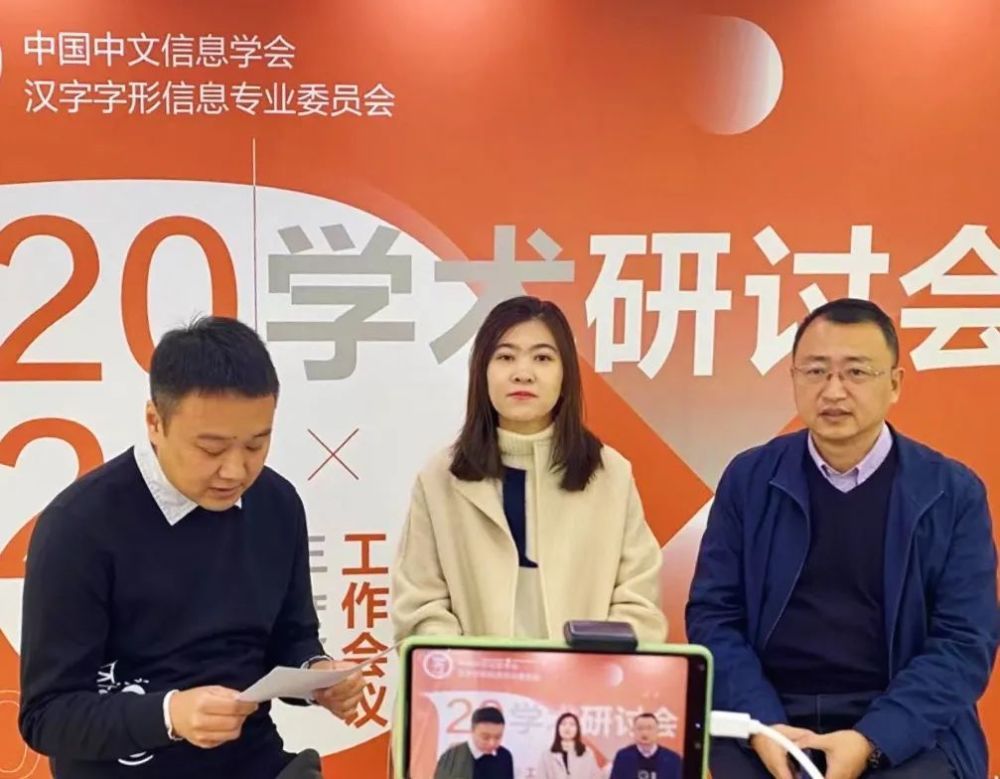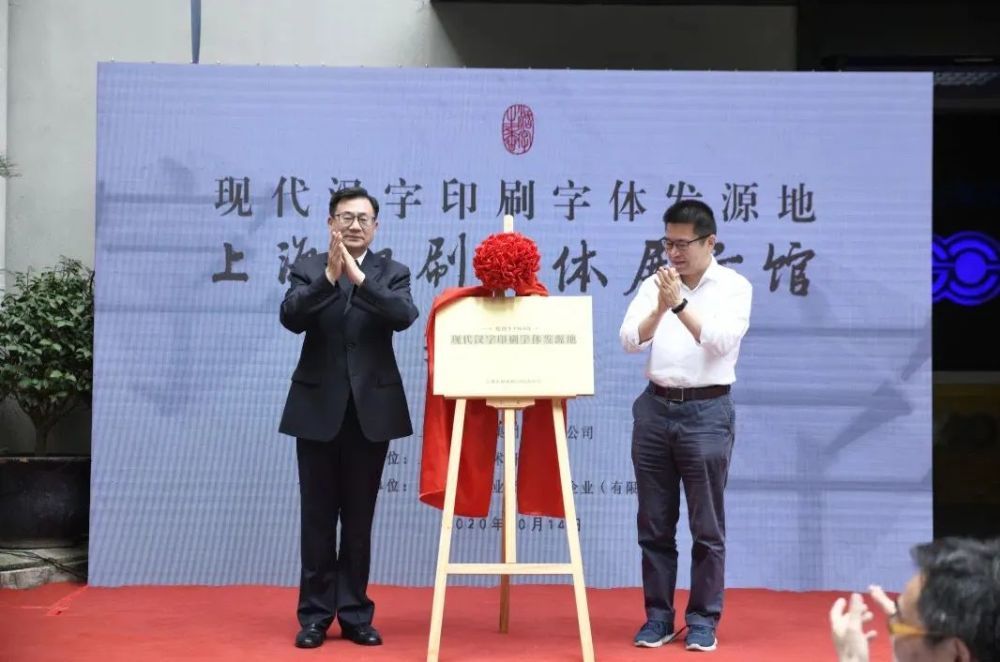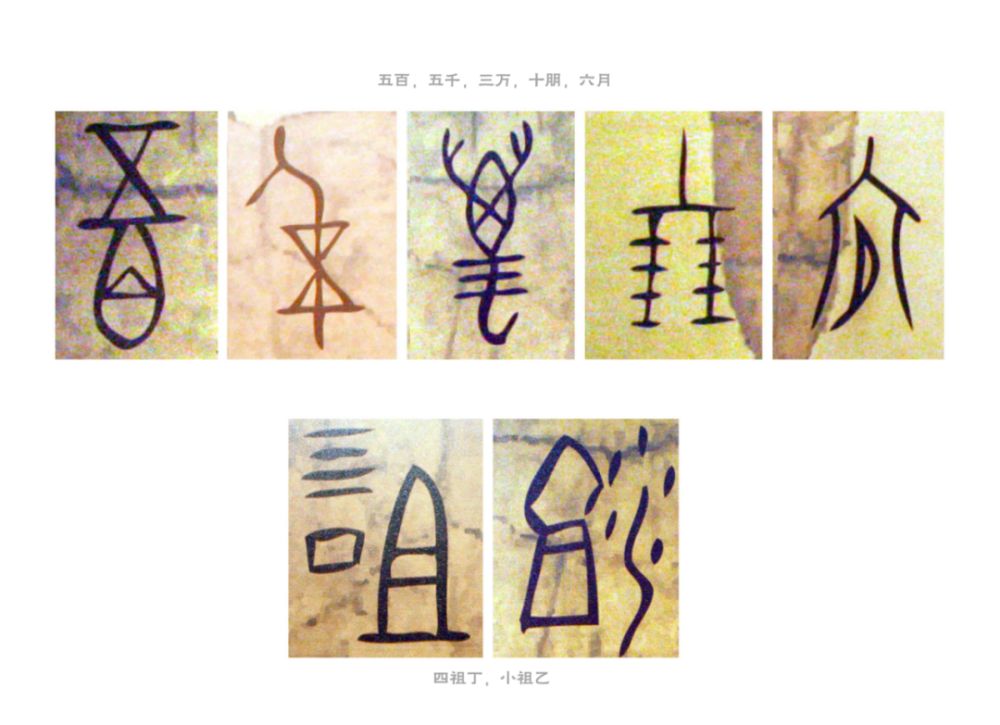
2020年汉字字形学术研讨会通过线上会议方式顺利举办
原文标题:干货回顾丨字体业者线上齐聚,共话文字设计新发展
12月6日,由中国中文信息学会汉字字形信息专业委员会主办的“中国中文信息学会汉字字形信息专业委员会2020年学术研讨会”圆满结束。数十位中文字形信息领域的专业从业者、研究者、字体厂商代表,以及两百多名来自全国各地的字体设计爱好者以线上会议的方式共同参加了此次学术研讨会议。
中国中文信息学会办公室主任肖千慧(中)出席会议并致辞
汉字是中华文化的基因和核心,是中华文明得以传承和发展的载体,而计算机中文字体是汉字书写文明在信息化时代的全新表现形式,也是中文信息处理的基础,是最具中国特色的知识产权产品。中国中文信息学会一直多方呼吁加强字库知识产权的保护。近年来,在各方的共同努力下,字库行业开始进入良性发展阶段。
肖千慧老师还表示:希望在专委会各位委员,在所有专业从业者、研究者的共同努力下,推动中文字形信息学科的发展,传递汉字之美,弘扬中华优秀传统文化。
下面,就让我们一起来回顾这场字体云盛会的干货内容吧~
《汉文正楷在东亚地区的传播、影响及再设计——纪念汉文正楷诞生90周年》
汉文正楷是1930年代在中国上海诞生的著名的楷体活字,共包含11种字号和样式,是民国时期的第一套足体的铅活字。
汉文正楷一经面市便颇受欢迎,不久便被日本芦泽印刷所、金田三省堂等购入到日本进行销售。日本活字工业、IWATA、MOTOYA等著名活字公司都进行过改刻,可以说日本的正楷字体深受汉文正楷的影响。这些改刻和再设计贯穿了铅字时代、照排时代和数字时代。并流传到中国香港、中国台湾和东南亚地区。
本次演讲对汉文正楷的历史进行了研究、展示,通过收集、整理跨越了90年的资料和文献,为汉文正楷的数字化再设计提供了详实的参考和依据。
为打破当时外国资本对楷体活字的垄断,郑午昌等人创办汉文正楷印书局,并委托中华书局编辑高云塍书写了八千多字楷书原稿,此为汉文正楷的缘起
佐藤敬之辅巨著《汉字》中记录了日本活字工业对汉文正楷进行改刻的内容,主要包含三个方向:1.扩大中宫,缩小字面;2.将撇捺斜钩等笔画进行了缩短;3.横笔画的斜度更加统一,增强字体的稳定性。
对汉文正楷的再设计,遵循了中国大陆楷书字体的规范结构及笔画特征,同时对原字不理想的部分进行了修整
《汉字印刷字体的文化传承》
作为国内最早建立汉字印刷字体书写基地——上海印刷技术研究所数十年来始终在努力宣扬、保护和传承字体文化的道路上坚守前行。今年10月上海印研所举行了“现代汉字印刷字体发源地”和“上海印刷字体展示馆”的揭牌仪式,希望通过追本溯源、还原历史,尽可能让更多的人走进字体、关注字体、了解字体。
字体设计作为一项文化传播性的工作,应该将其纳入到美育的行列中,具有前瞻性和延展性的教学理念是推动行业发展振兴的关键性因素,能全方位的培养人才,夯实行业基础,在将文化与设计不断相融合的过程中,也引导大众建立起正确的字体文化属性,了解字体以及字体设计背后的故事,提高字体设计专业领域的社会认知度,将我们的汉字文化代代相传。
上海印刷技术研究所为现代汉字印刷字体的创写与发展做出突出贡献
“现代汉字印刷字体发源地”和“上海印刷字体展示馆”的揭牌仪式
上海印刷字体展示馆
《中国佛教文化字体设计(对佛经手抄本和刻本研究进行数码复刻)》
佛教是中国最具影响力的一个教派,二千多年来,对我国的各个领域都产生了深刻的影响,书法作为一个特殊艺术形式也不离外。在印刷术出现之前,僧人、信徒在读经之余抄写经文,以此来传播佛教的教义和扩大佛教的影响。由于纸、帛易于损坏,不便保存,就有一些佛教徒把经文刻在山崖或石碑上。在印刷技术出现后,佛教徒也通过刻制经板印刷经书的方式进行传播。
写经和刻经,对中国书法艺术和印刷技术都有着深远的影响,通过对古代经典进行研究来探索现代汉字设计新的可能性。传统文字、文物受载体的限制难以保存和展示,字体文物存在永久性损坏或遗失的风险。
本次演讲展示了通过对古代经典写经、刻经进行复刻,将文字文物转化为数码字体的研究成果,希望能够利用字库产品在互联网环境中的通用易用的性质,使文物的文化价值得到最大化的传播和体验。
汉仪敦煌写经的佛经写本原型文字
汉仪北魏写经的复刻对照
汉仪金陵刻经字体
《北碑正书 | 设计思维下的多域文明碰撞》
北碑正书以方笔入字,将笔画的婉转变化,起承转合,用刀刻直线转折,代替笔画线条转折。壮其胆、强其骨、厚其力、生其势。其灵感来源于北魏诸家碑体,与古苏美尔人的楔形文字。本次演讲通过展示北碑正书的设计过程,呈现现代思维下的多领域(古今、中外)文明的碰撞。
北碑正书
为字体添加视觉锚点的两种情况
北碑正书字形展示
《最新中文字体设计交流与分享-互联网与智能时代汉字字形探索与研究》
字玩实验室是锐字旗下一个致力于探索汉字创新设计与研究的实验室,探索汉字的N种可能,研究汉字设计的未来发展趋势,研究汉字设计与新场景与新技术的融合。本演讲分享了字玩实验室的一些字体研究成果:
1.字玩实验室推出了全球第一个智能代码72变系列化中文字库,字玩汉字设计引擎可以一键生成符号、标准中文编码的新字形。
2.字玩不明黑与字玩不明宋是在现有汉字构成规律的基础上,字玩实验室尝试做出一些新的汉字字符,这些字符即保留了已有中文的特征,也有独特的组合方式。另外,通过不同部件的结合方式,也让这些新字符营造出不同程度的熟悉感或陌生感,字玩不明黑与字玩不明宋采用中文5000个字对应的编码生成字库,可以直接使用与应用到文化衍生设计中。
3.字玩翻滚积木彩色字库是全球第一款中文彩色积木字库,采用中文简体标准编码,可以直接使用Adobe及支持彩色字库的软件上使用,可以自定义专色。彩色积木字库是在探索黑白字体与场景新字形的一种新的尝试。
锐字字玩不明黑
锐字字玩不明宋
字玩翻滚积木彩色字库
《女书的数字化——Noto女书传统体》
女书是西南地区的用于记录湘南土话的非汉文种,曾流行于湖南江永部分地区的汉族和瑶族的妇女之间进行秘密通信与当地民歌歌词的记录。该文种于20世纪80年代被报道后,随着方言研究热潮被方言学界重视,又因其使用群体的特殊性而被民众关注。
2017年女书正式进入Unicode标准。本项目在细致研究与设计美学的双重支撑下以Unicode相关规定为标准设计传统风格的女书字体家族,包括三个字重,并考虑未来产出可变字体。本次演讲展示了女书的基本知识和字体的创作过程。
女书的异体字
字符分离
修正字体码表错误
女书传统体可变字体效果
《卡通字体的探索和研究——华光半糖体的创作心得》
动漫不仅是给孩子看的,同样,卡通字体的受众群体也不局限于儿童。卡通字体可以不必那么的稚幼,华光半糖体便是一款老少皆宜的卡通体。华光半糖体的创作灵感来源于半糖主义,一种健康的生活理念,甘苦相伴也正是这个时代所正在经历的过程,健康积极的面对,一切都是那么阳光。
卡通字库有着工业化的制作流程,成品效果却要呈现出自然随性,如何可以做到这一点呢?解放字框,打破常规,本次演讲通过分享华光半糖体的字库创作过程,探讨了如何设计出自带韵律感和节奏感的卡通字库。
华光半糖体——大小不一的字面设计
华光半糖体——字体灰度一致
华光半糖体——字身框、字面框规范的多变
《合文&字体设计》
本次演讲以文字学“合文”概念为基础,讨论汉字中与此相关的造字现象及构字原理;梳理合文规律在汉字及字体设计中的应用;分析传统民间与当代人士利用其原理所做的合文字体设计,并尝试总结合文字体的一些创意性设计规律。
原始文化中的一些“合文”现象
以“孔孟好学”为例分析“合文”规律和方法
“合文”在LOGO设计中的应用
《中文可变字体的设计开发与应用》
可变字体格式自2016年ATypI公开发布至今已经4年,但在市面上的中文可变字体产品还不多见。本演讲从可变字体的优点与应用发展、中文可变字体的变化设计、设计师对可变字体的看法与期待、现有操作系统平台与软件的支持等四个方面,分享了开发多套中文可变字体的经验,以期与业界共同来推广中文可变字体的开发与市场应用。
可变字体在电子书萤幕显示中的应用
可变字体在互动式网页设计中的应用
三款文鼎VF晶熙黑体支持不同维度的可变
《怪物之名》
近年来,一种小众的字体风格再度流行,受到了诸多平面与字体设计师的热烈追捧,似乎一股新兴的设计浪潮正蓄势待发。这种字体风格常被称作逆反差(reverse contrast)。经过逆反差处理的字体,能营造出比起普通字体更夸张、更怪诞、更具张力的视觉效果,以逆反差字体为素材的平面设计能表达更富有情绪、更戏剧化的画面。作为一款起源于西方,在东方土地上茁壮成长的字体风格。从最早的被称为“怪物”的西文逆反差、流行于日本「新年贺卡」的扇尾体到风格强烈的漆书和民国年间丰富多彩的美术字。
本演讲对其诞生、演化到在东亚本地化的历史进行了梳理,试图从这些历史的碎片之中还原这个曾经被视作“怪物”的字体应有的风貌。并结合三言2020年发布的全新字体家族「基本美术体」的设计,谈一谈在信息爆炸的今天,为何我们要选择研究和设计一款基于西文字体而发展出来的字体家族;回顾这种字体风格演化的进程,是否又能为我们的字体创新带来新的养料。
逆反差字体的源流与现代化创新
书法、印刷界对逆反差字体的评价
基本美术体的多维可变效果演示
学术研讨会结束后,中国中文信息学会汉字字形信息专业委员会年度工作会议召开,汉字字形信息专业委员会主任张建国主持召开了工作会议。会议上,各位委员就字体设计的新方向、字库新技术与新玩法、面临的新困境与挑战,以及如何加强设计领域深度合作等话题进行了交流与探讨,并对未来的工作做出了规划与展望。
中国中文信息学会汉字字形信息专业委员会希望通过每年的学术研讨会及工作会议,能够让更多的从业人员彼此交流、分享成果,从而推动字体行业实现更好的发展,透过字体,传承发扬中华文化,助力汉字走向世界!